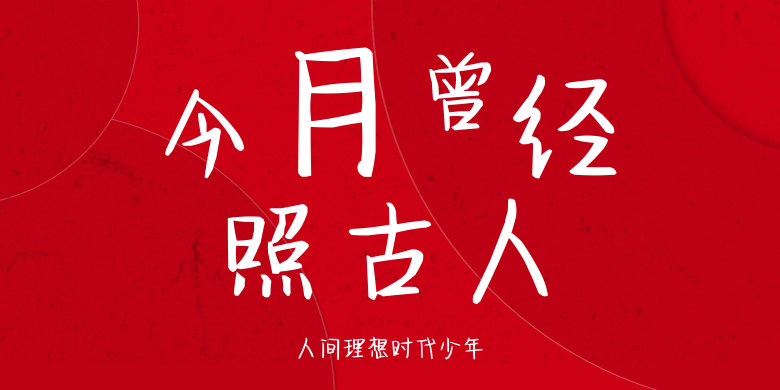
人间理想时代少年
人间理想时代少年,这款字体结构工整、笔画清晰,兼顾美观与易读性,适用于标题、正文、海报、包装、LOGO 等多种场景。字形优雅稳定,风格百搭耐看,适配日常排版与创意设计,让文字呈现更舒适、更具质感。人间理想时代少年一笔一画,皆是细节,以均衡的比例、流畅的线条打造舒适视觉体验,字形端正大气,风格简约现代。无论是商业设计、品牌宣传还是日常排版,都能轻松驾驭,让文字更有格调与力量。人间理想时代少年字体下载。